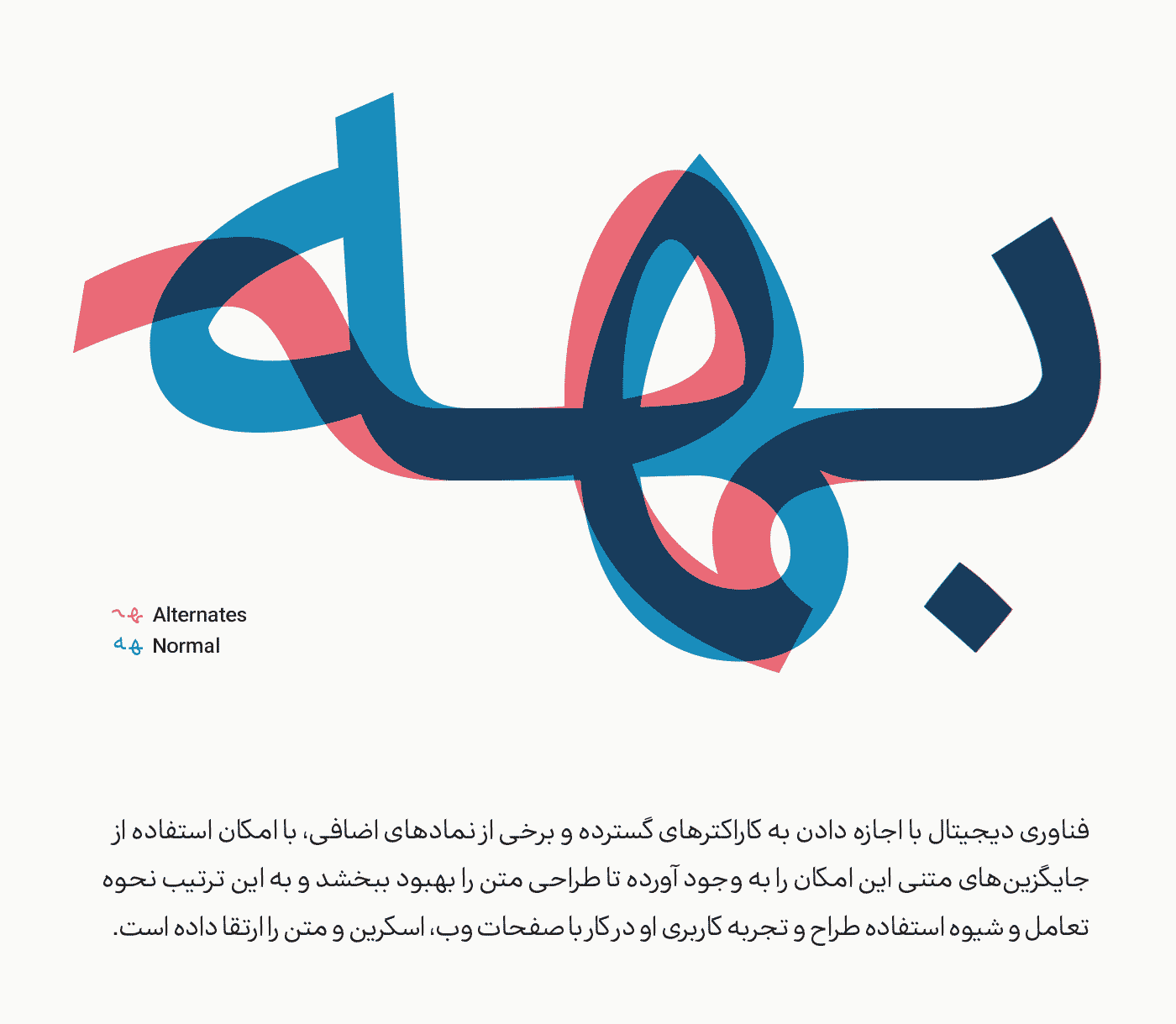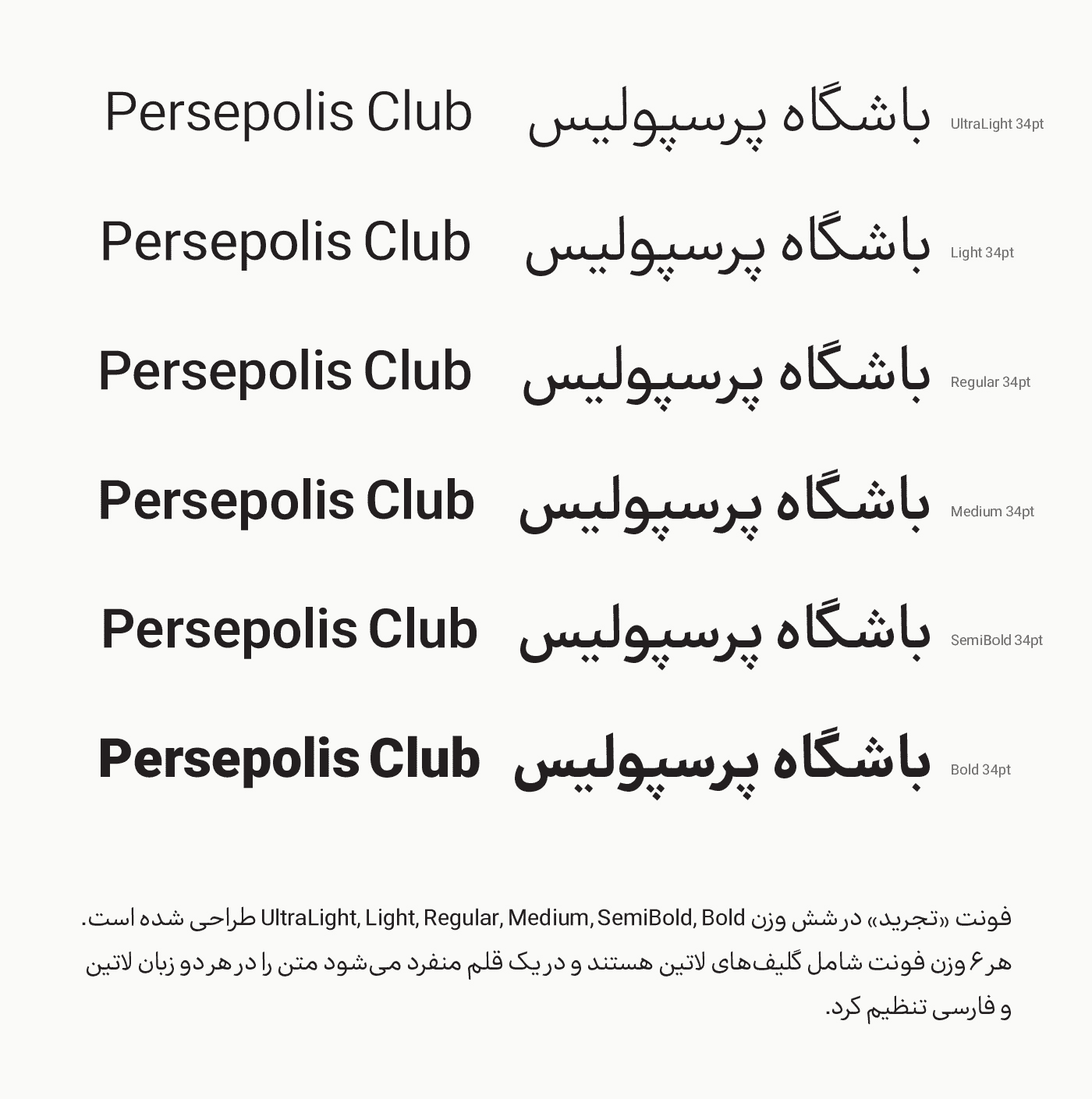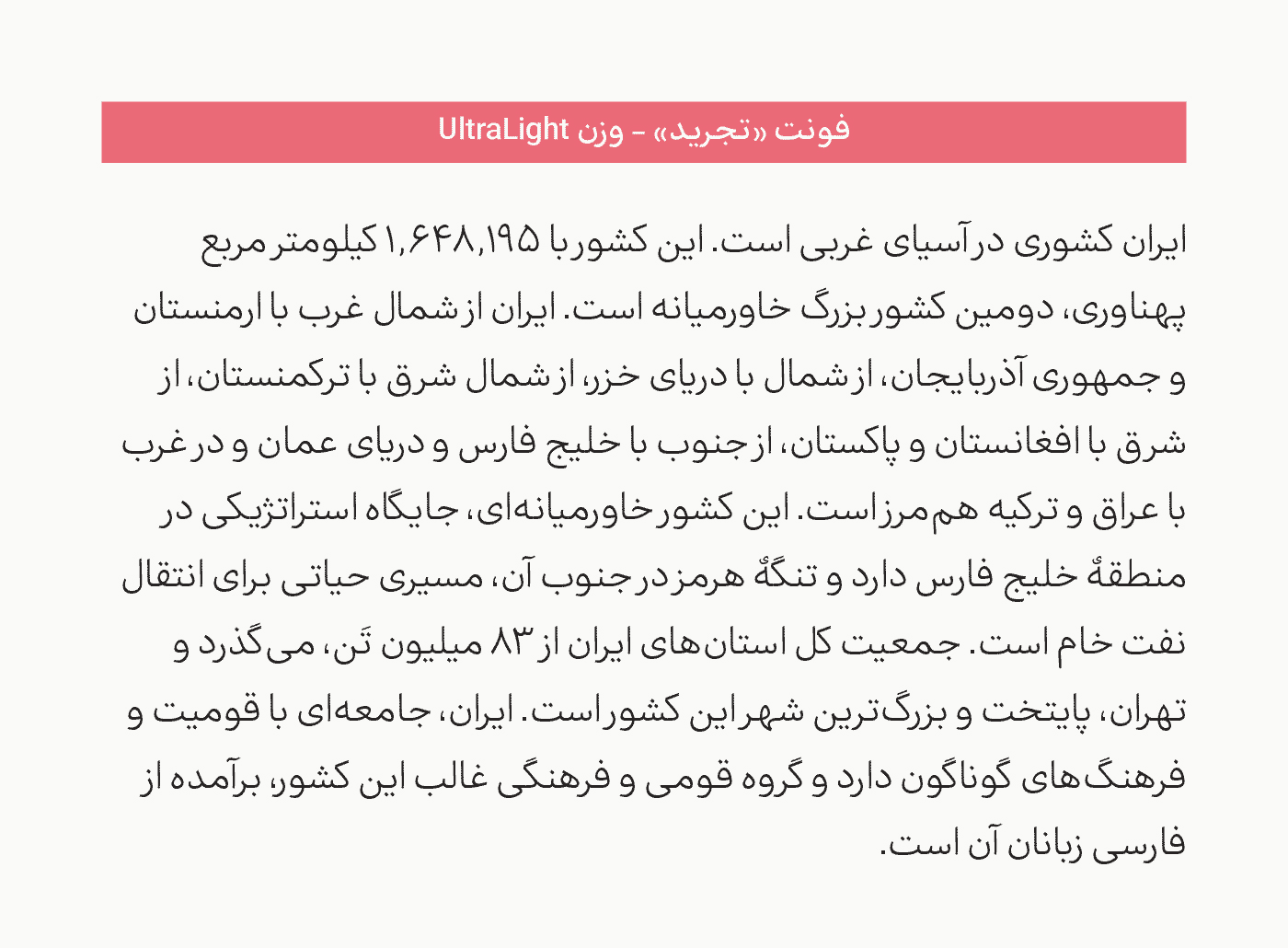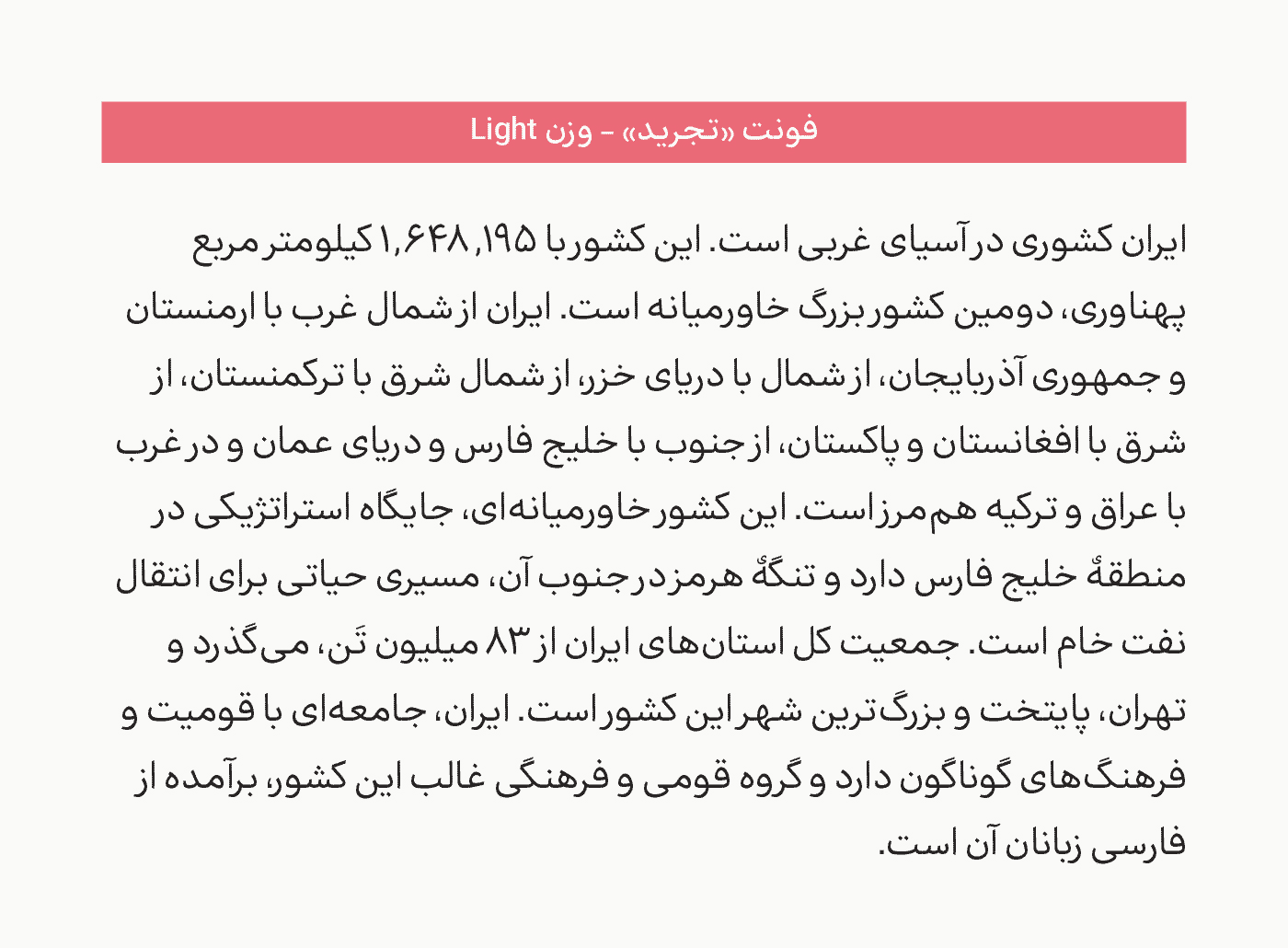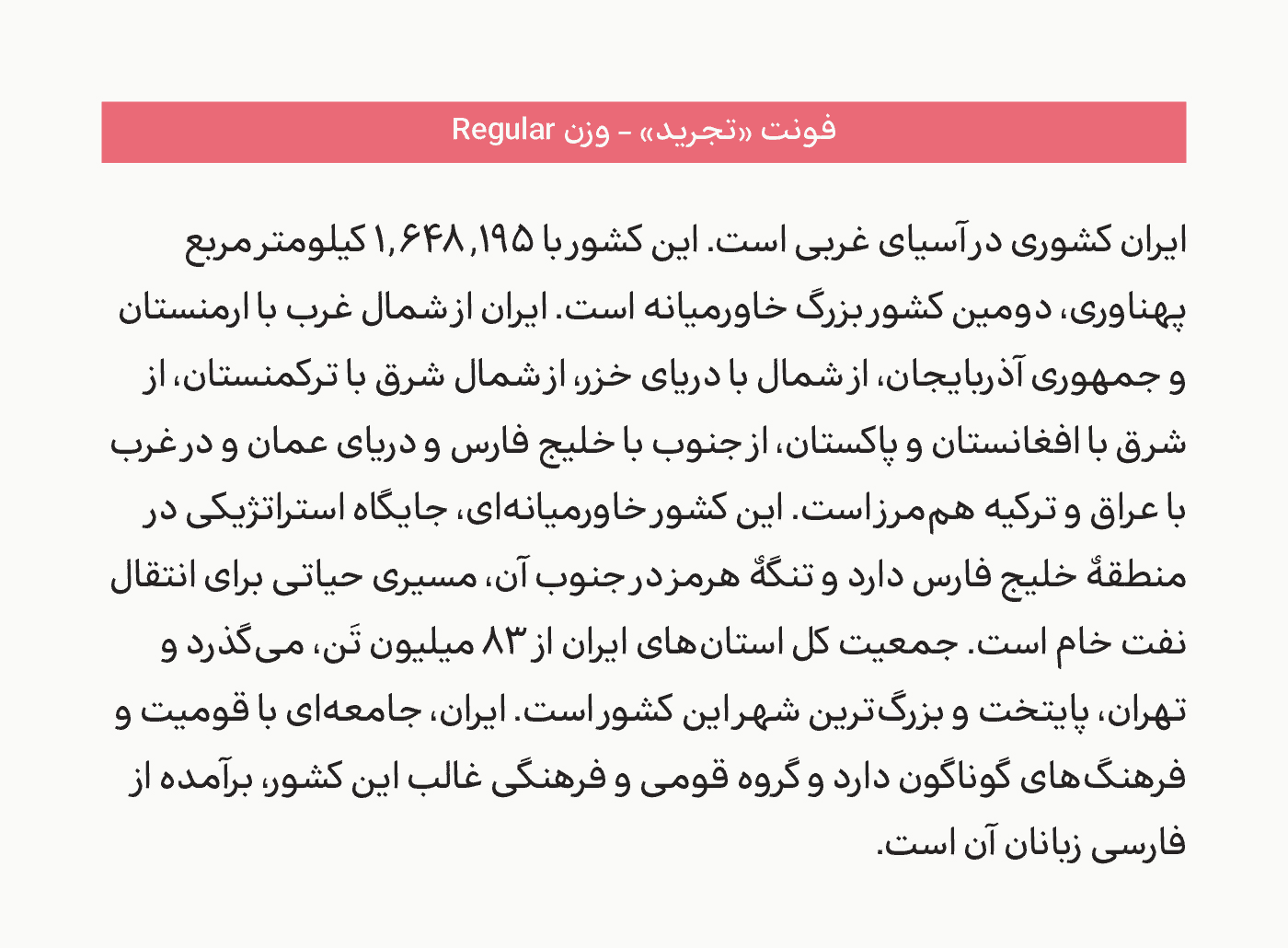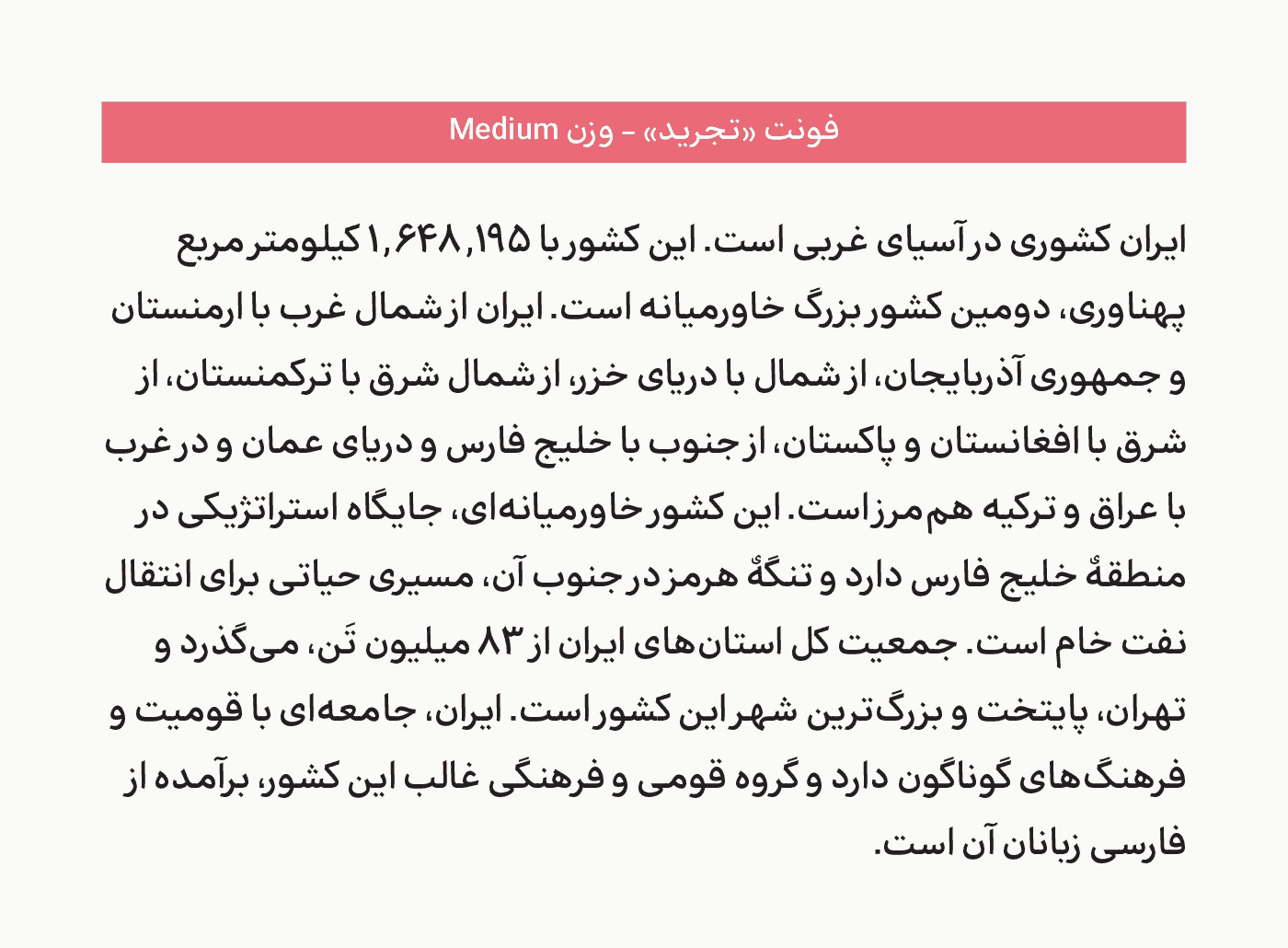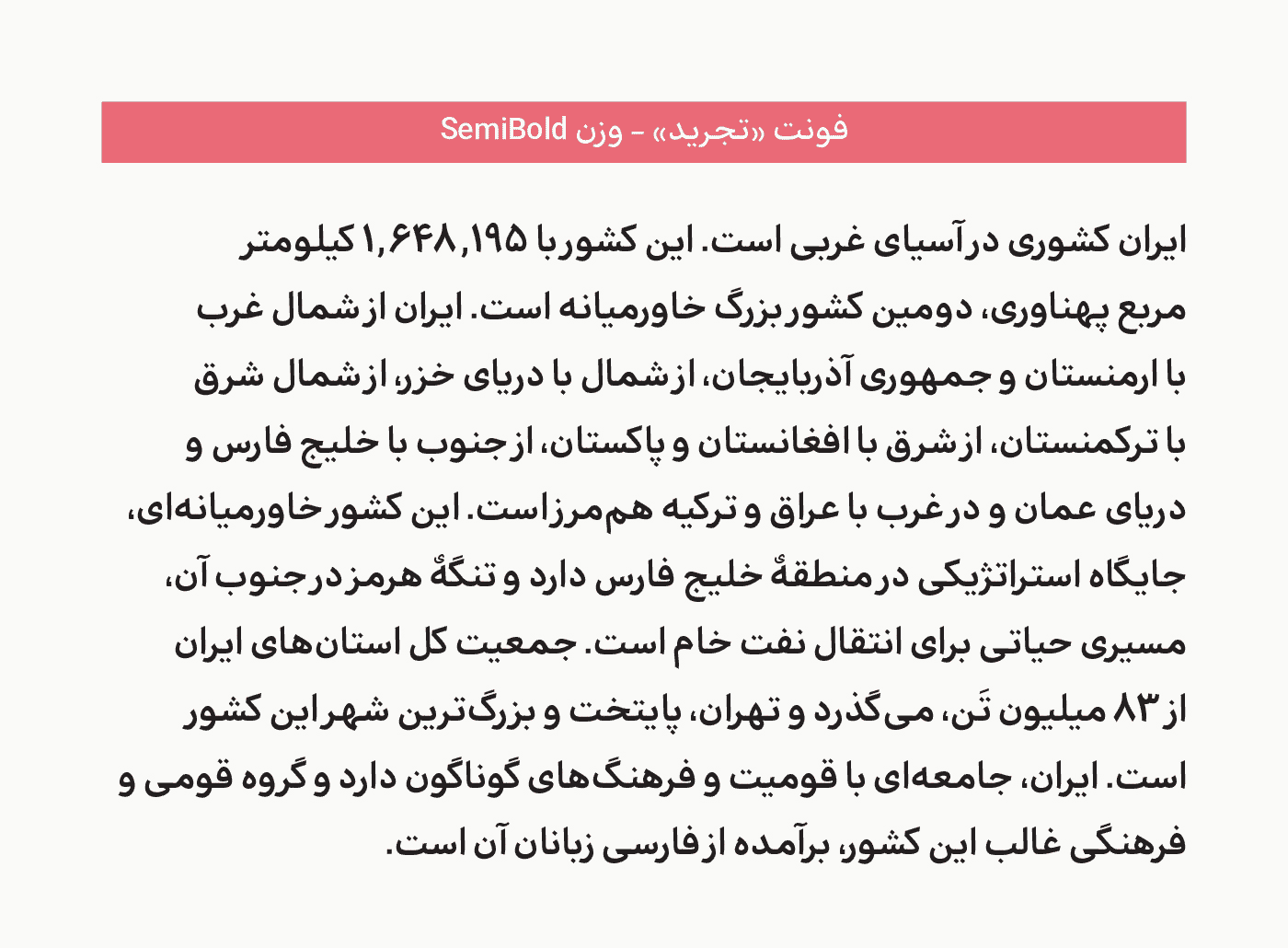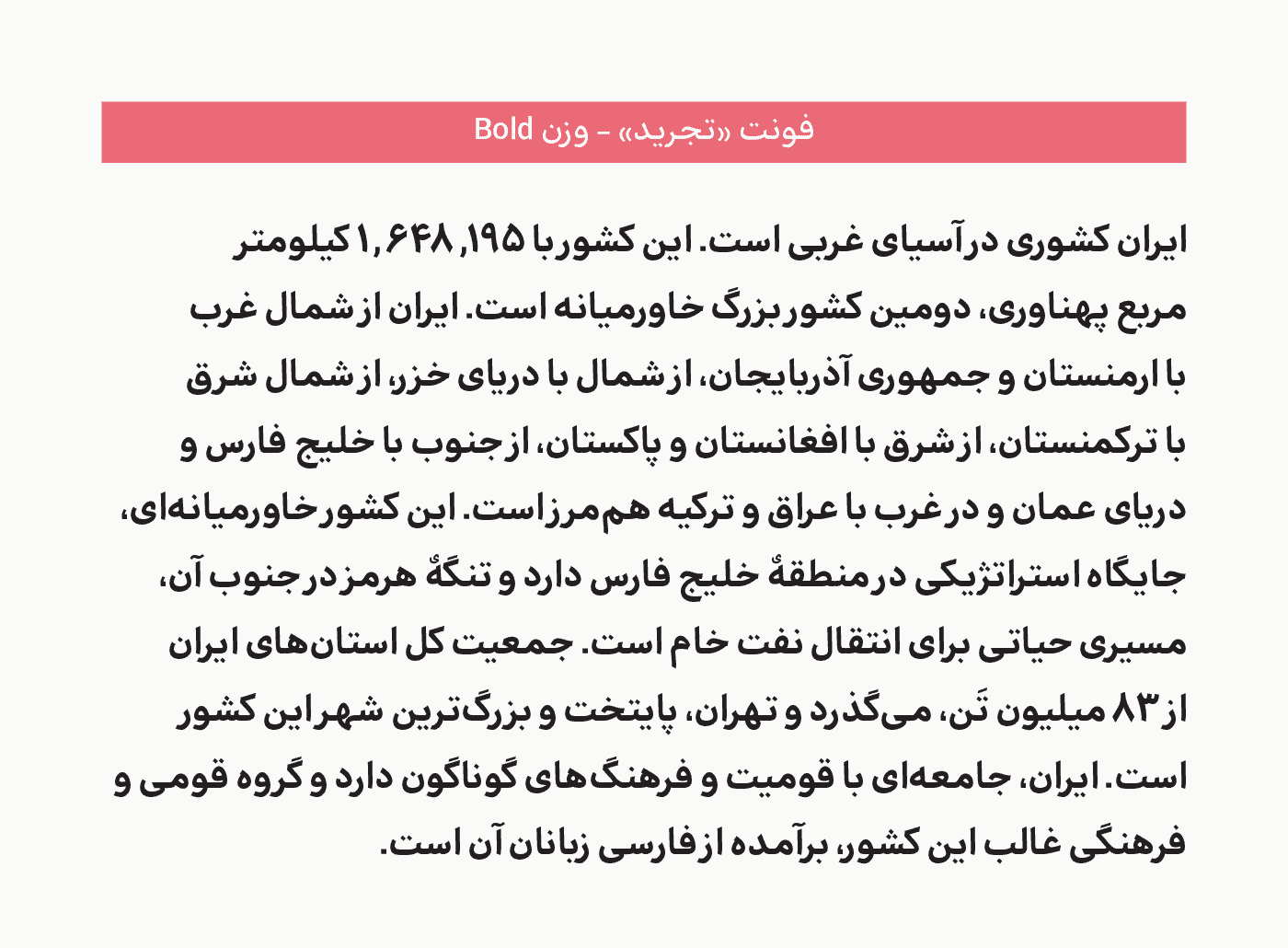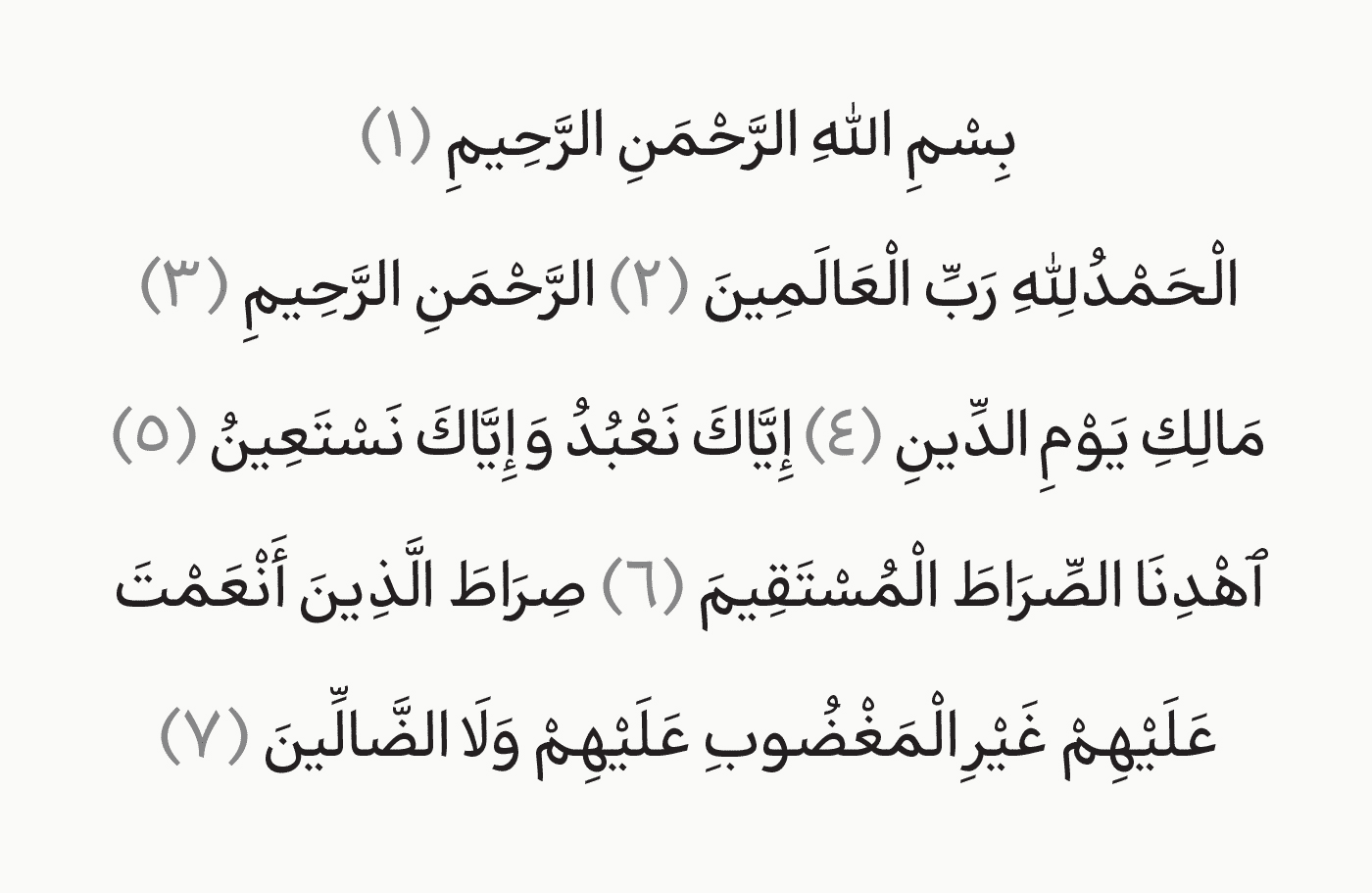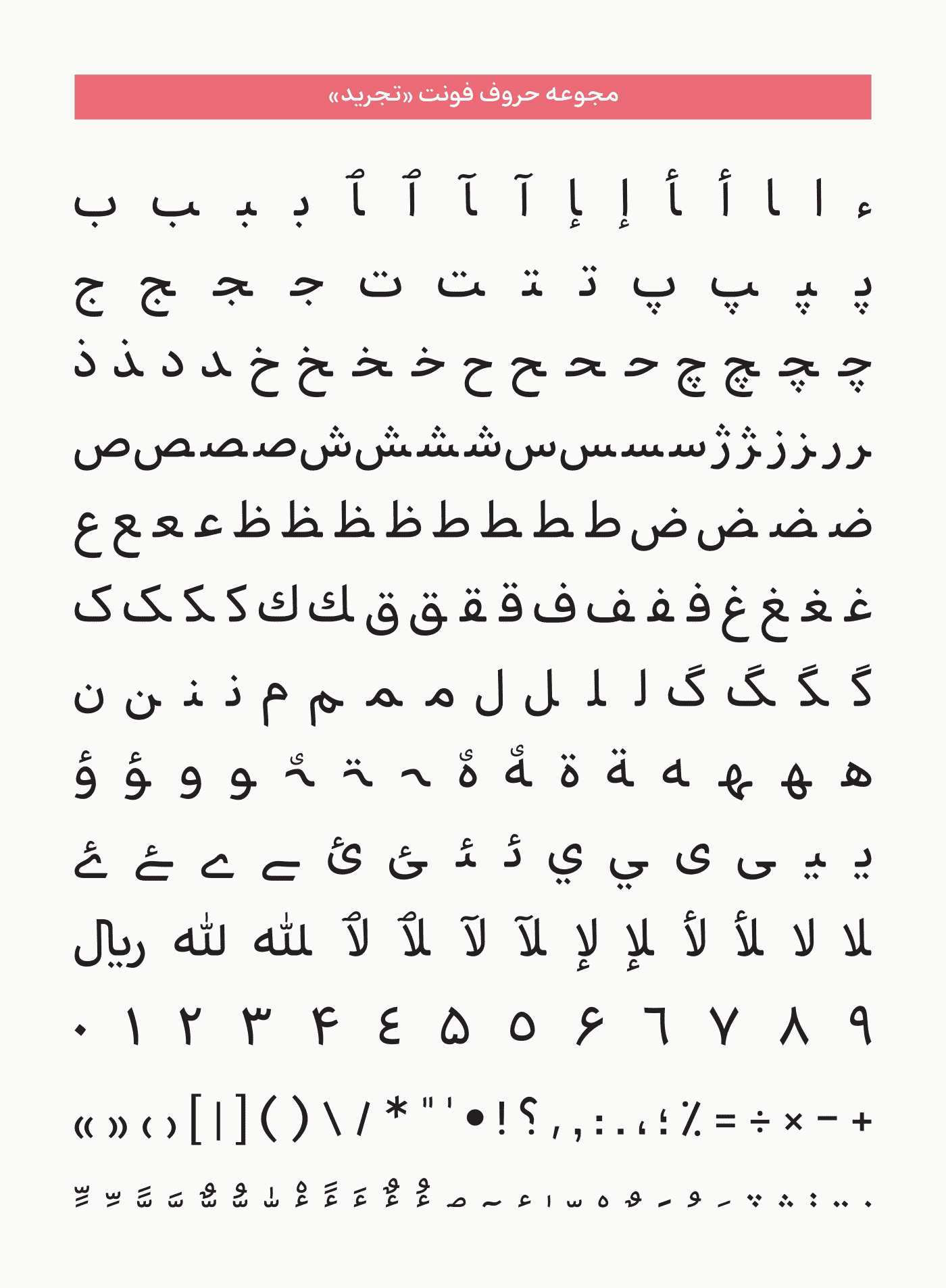
این فونت از زبان فارسی، عربی و انگلیسی پشتیبانی میکند.
ویژگیهای اوپنتایپ
فونت تجرید در قالب اوپنتایپ و ویژگیهای این قالب طراحی و تولید شده است. «تجرید» با تنظیم فواصل و کرنینگهای متناسب به متن جلوهای پویا بخشیده است. فناوری دیجیتال با اجازه دادن به کاراکترهای گسترده و برخی از نمادهای اضافی، اعرابگذاری دقیق و همچنین با امکان استفاده از جایگزینهای متنی این امکان را به وجود آورده تا طراحی متن را بهبود ببخشد و به این ترتیب نحوه تعامل و شیوه استفاده طراح و تجربه کاربری او در کار با صفحات وب، اسکرین و متن را ارتقا داده است.
خانوادهی فونت تجرید
فونت تجرید در شش وزن UltraLight, Light, Regular, Medium, SemiBold, Bold طراحی شده است. هر ۶ وزن فونت شامل گلیفهای لاتین هستند و در یک قلم منفرد میشود متن را در هر دو زبان لاتین و فارسی تنظیم کرد. «تجرید» مجموعه کاراکترهای اصلی لاتین را شامل میشود و از همه زبانهایی که از خط فارسی استفاده میکنند پشتیبانی میکند. اینها شامل عددی جدولی و متناسب عربی، فارسی و اردو و مجموعه ای از اعداد جداول اروپایی (لاتین) است. قلم «تجرید» طبق استاندارد جهانی یونیکد ساخته شده و در تمامی محیطهای متنی و نرمافزاری که از خط فارسی پشتیبانی میکنند قابل استفاده است.